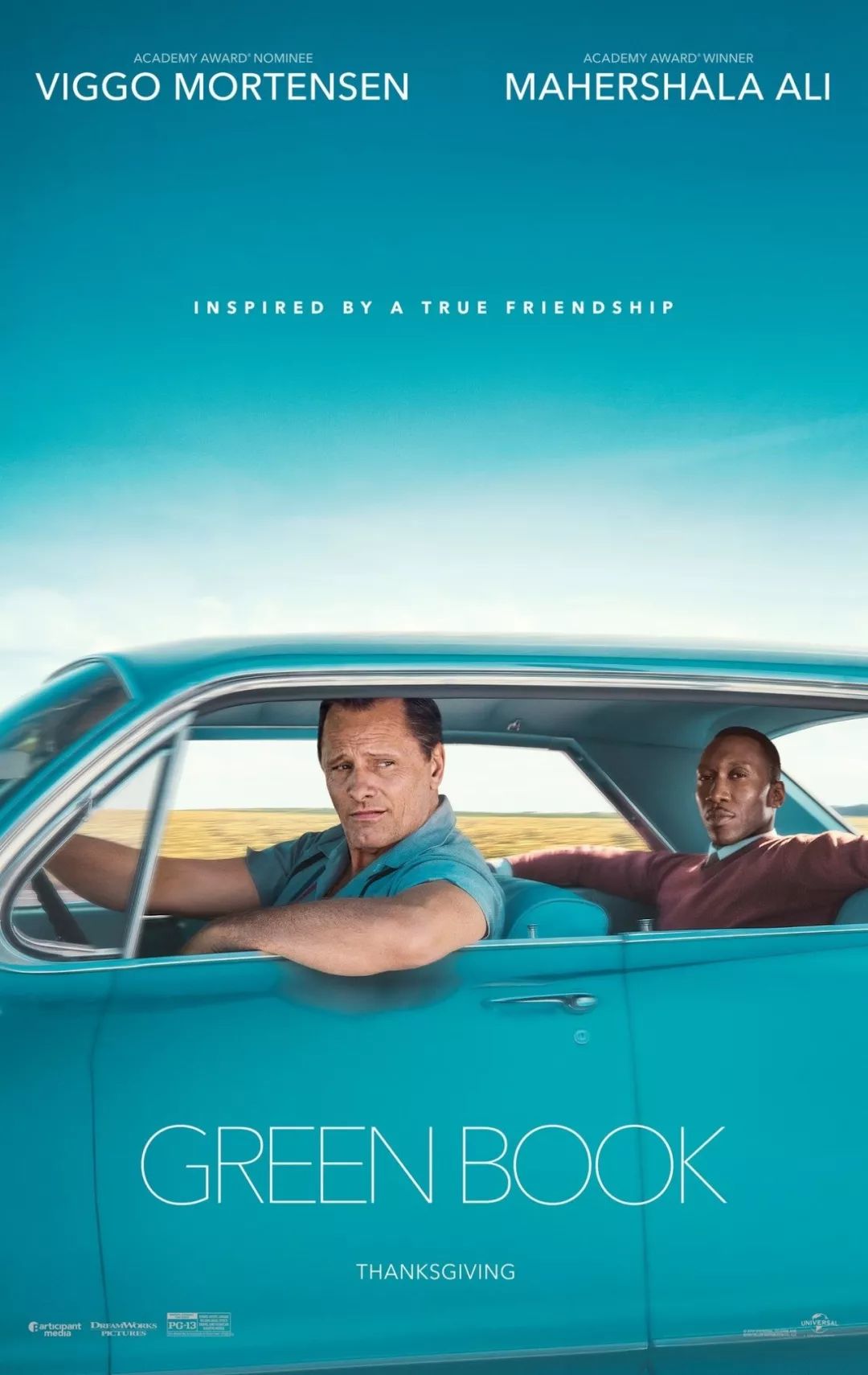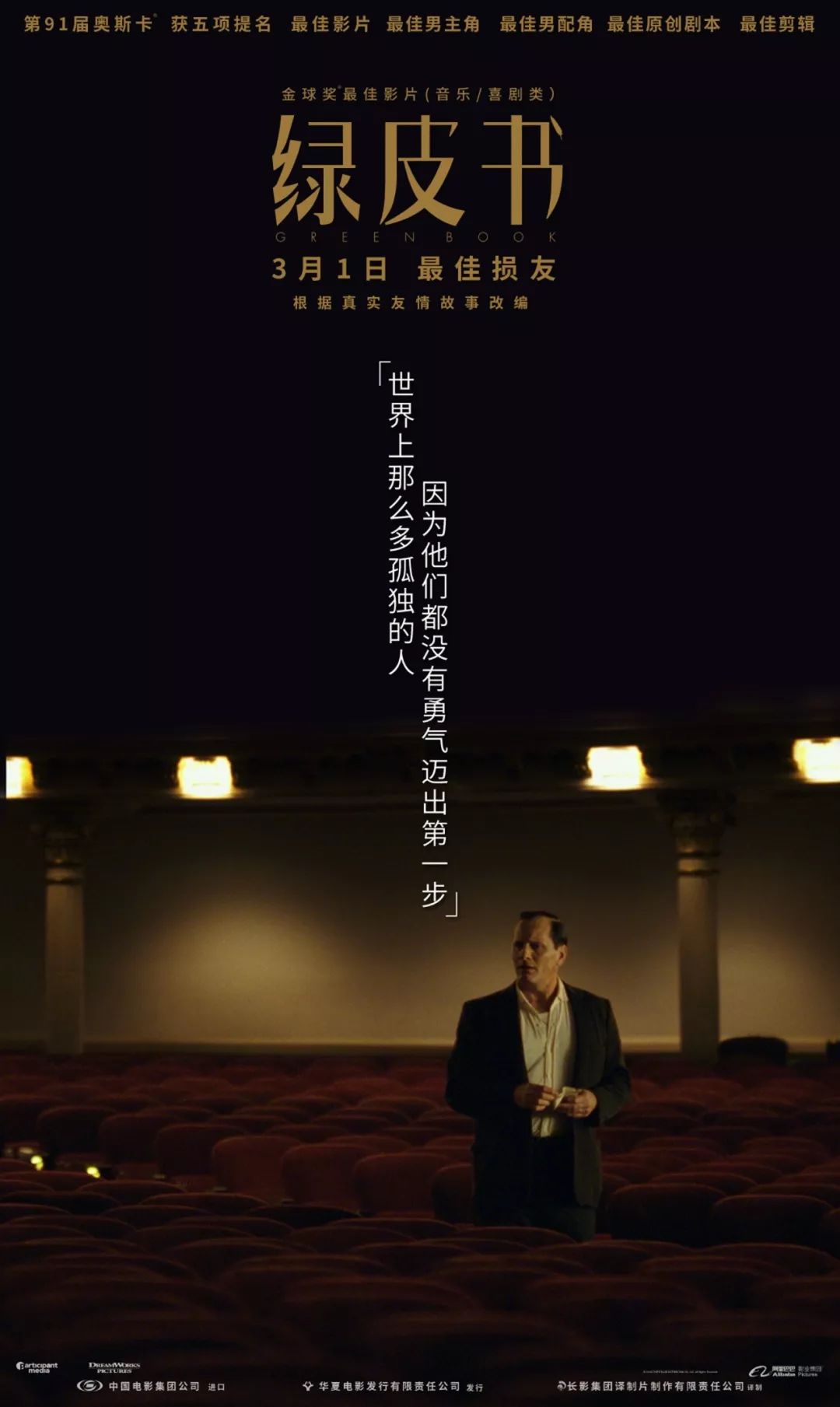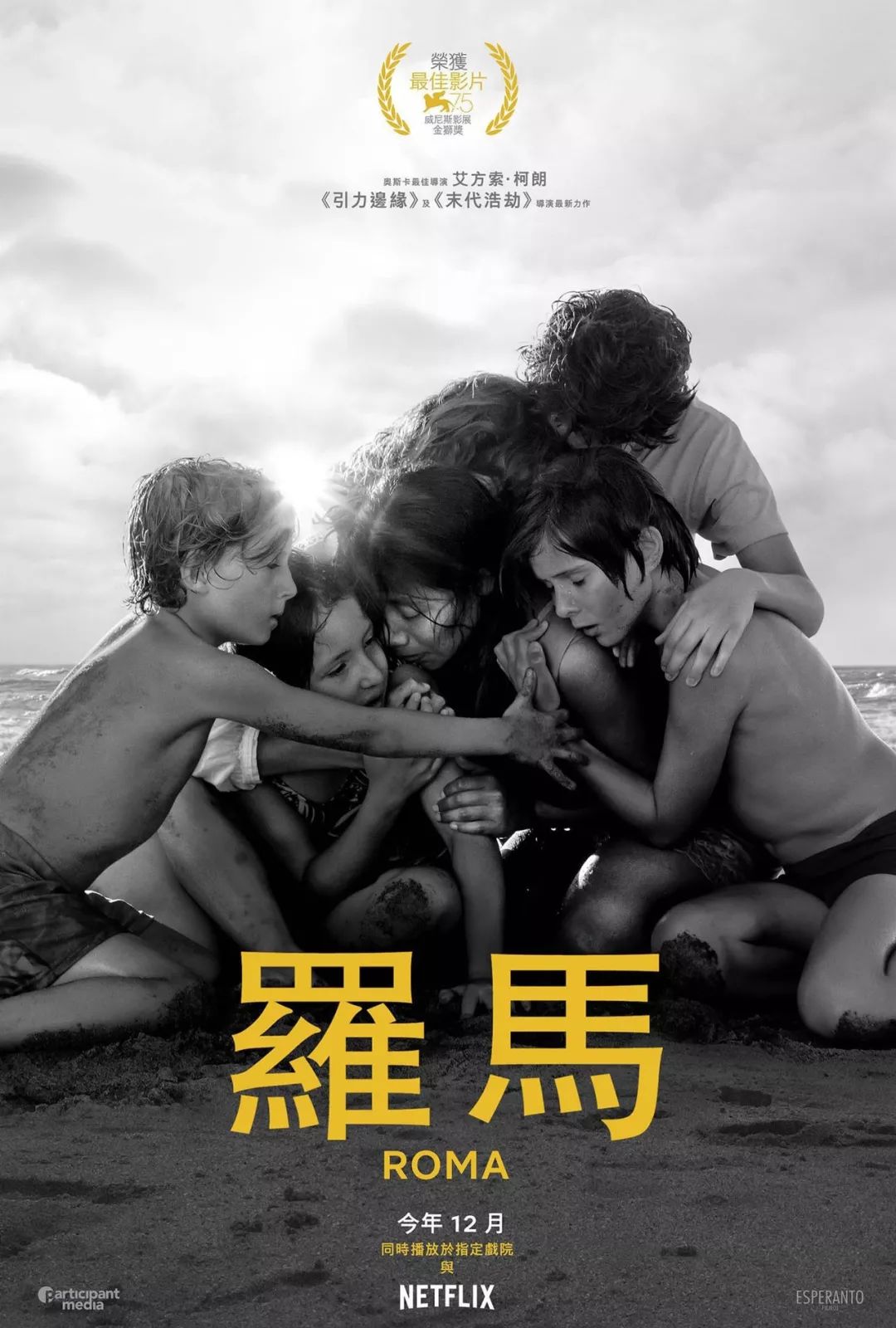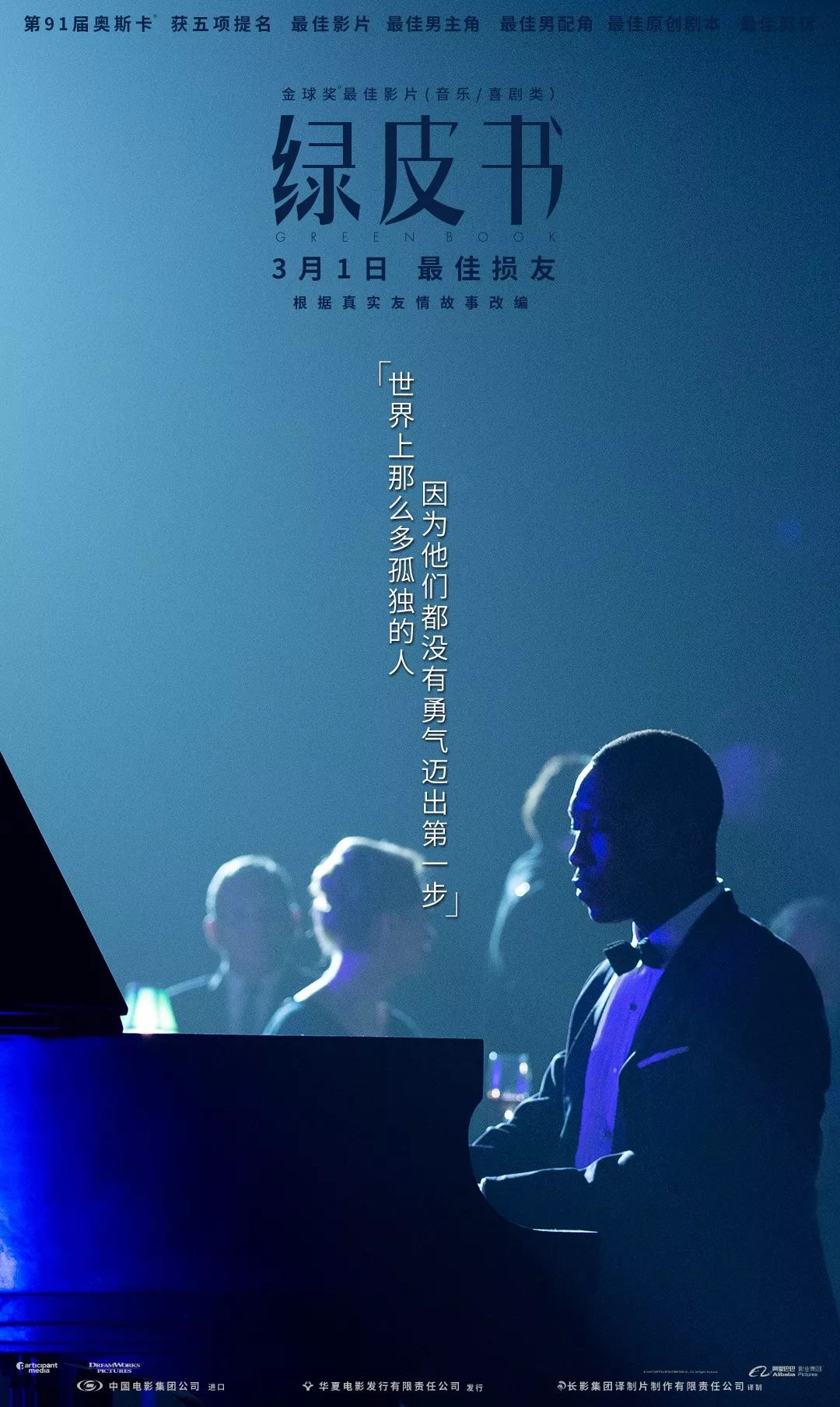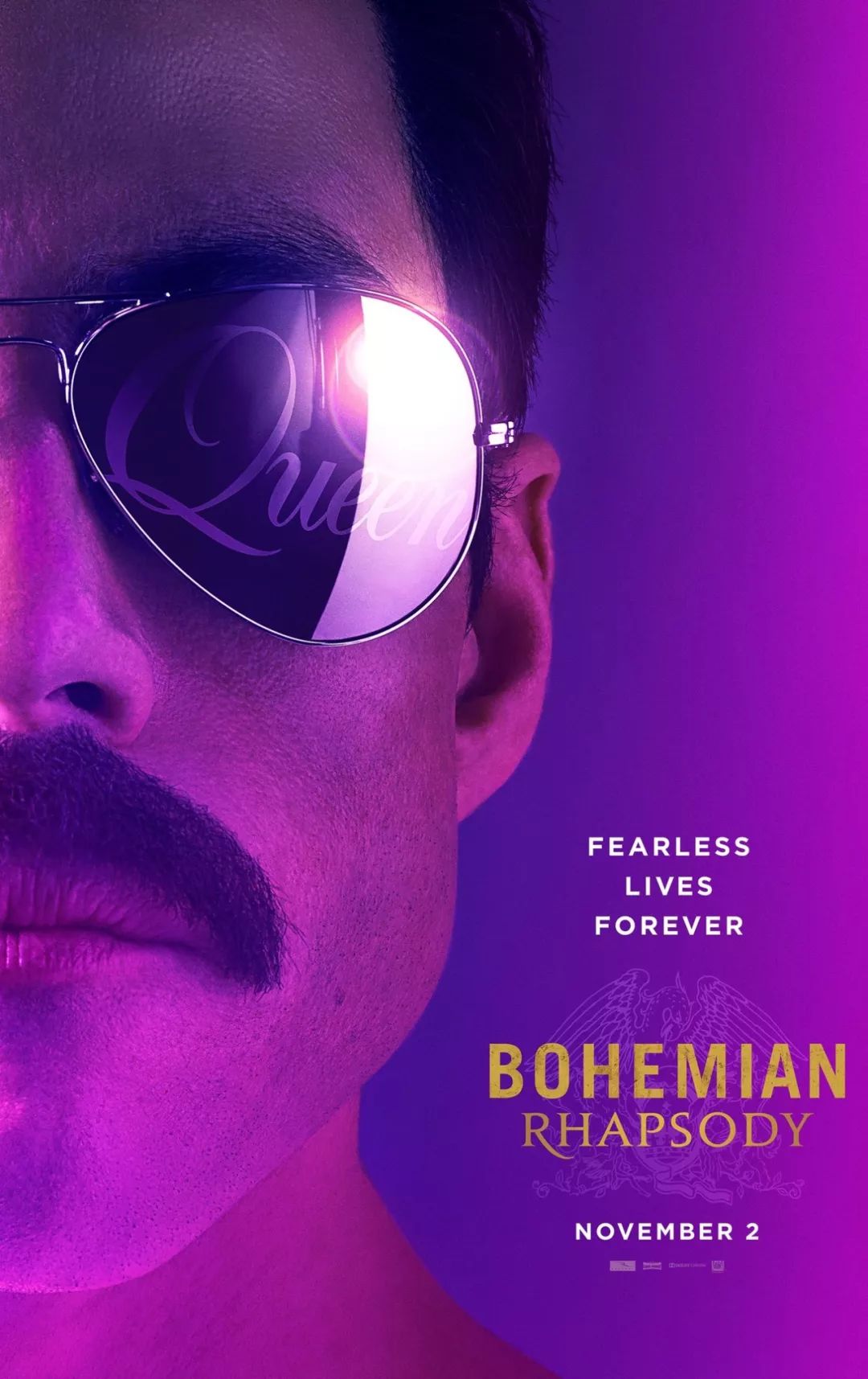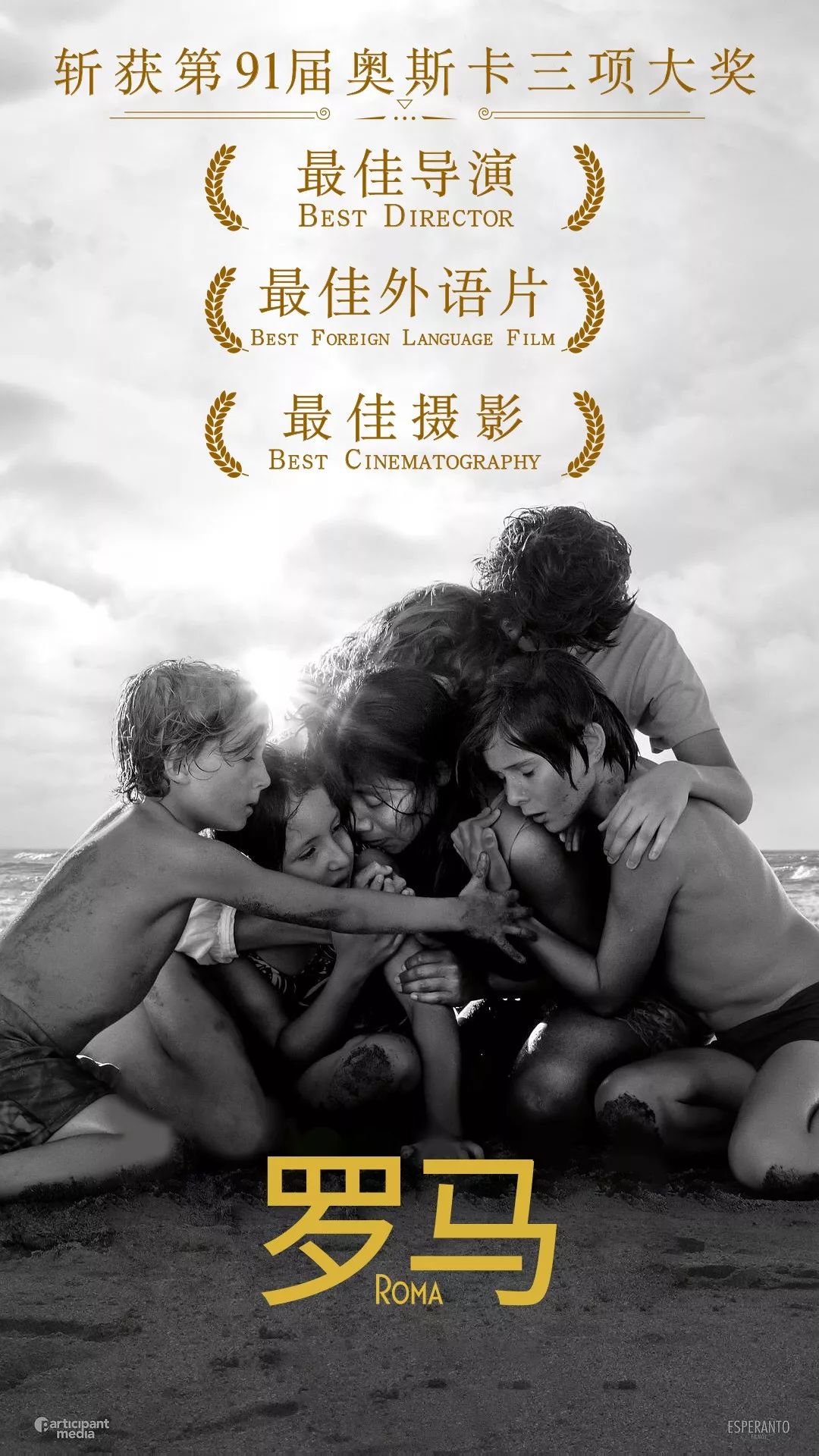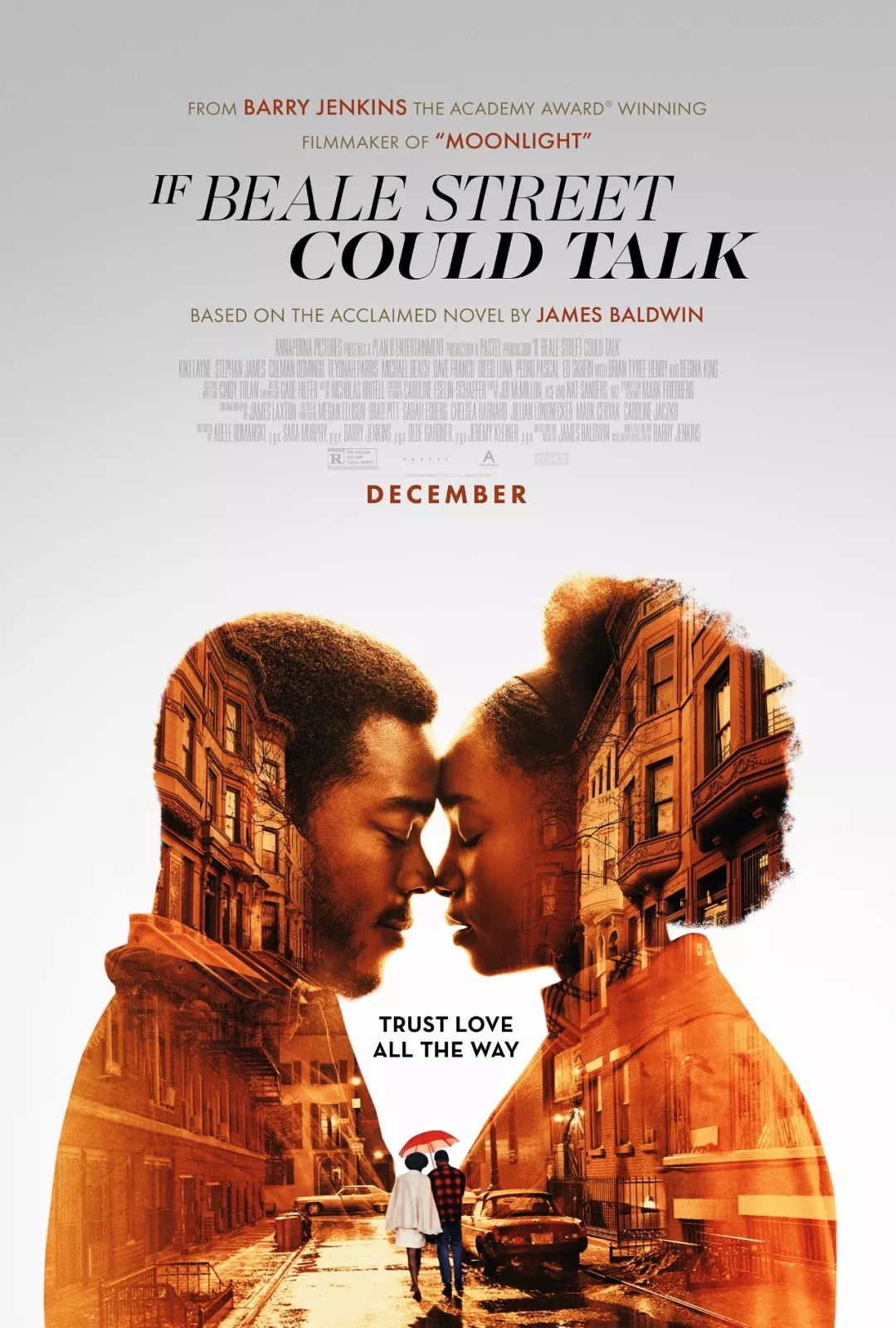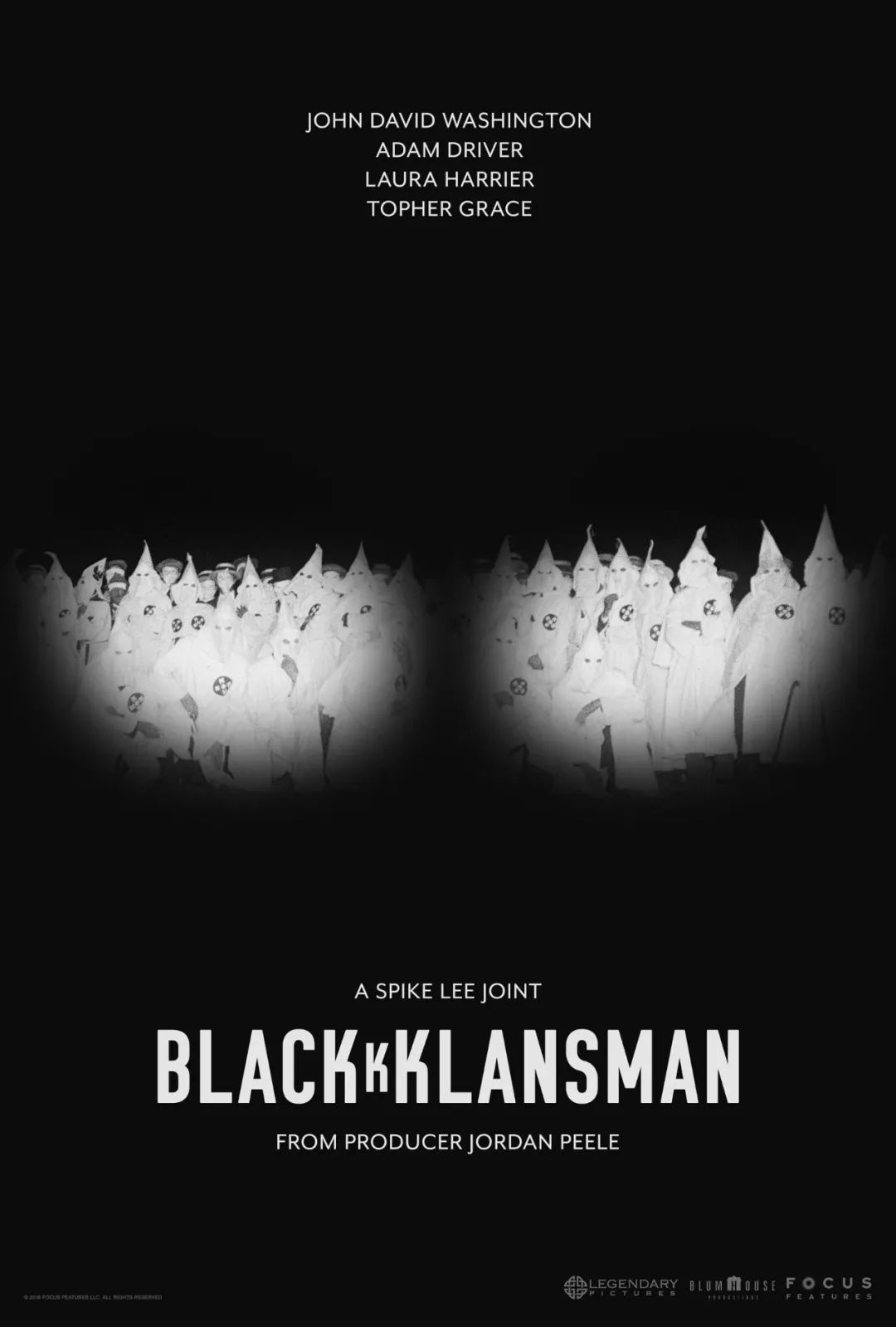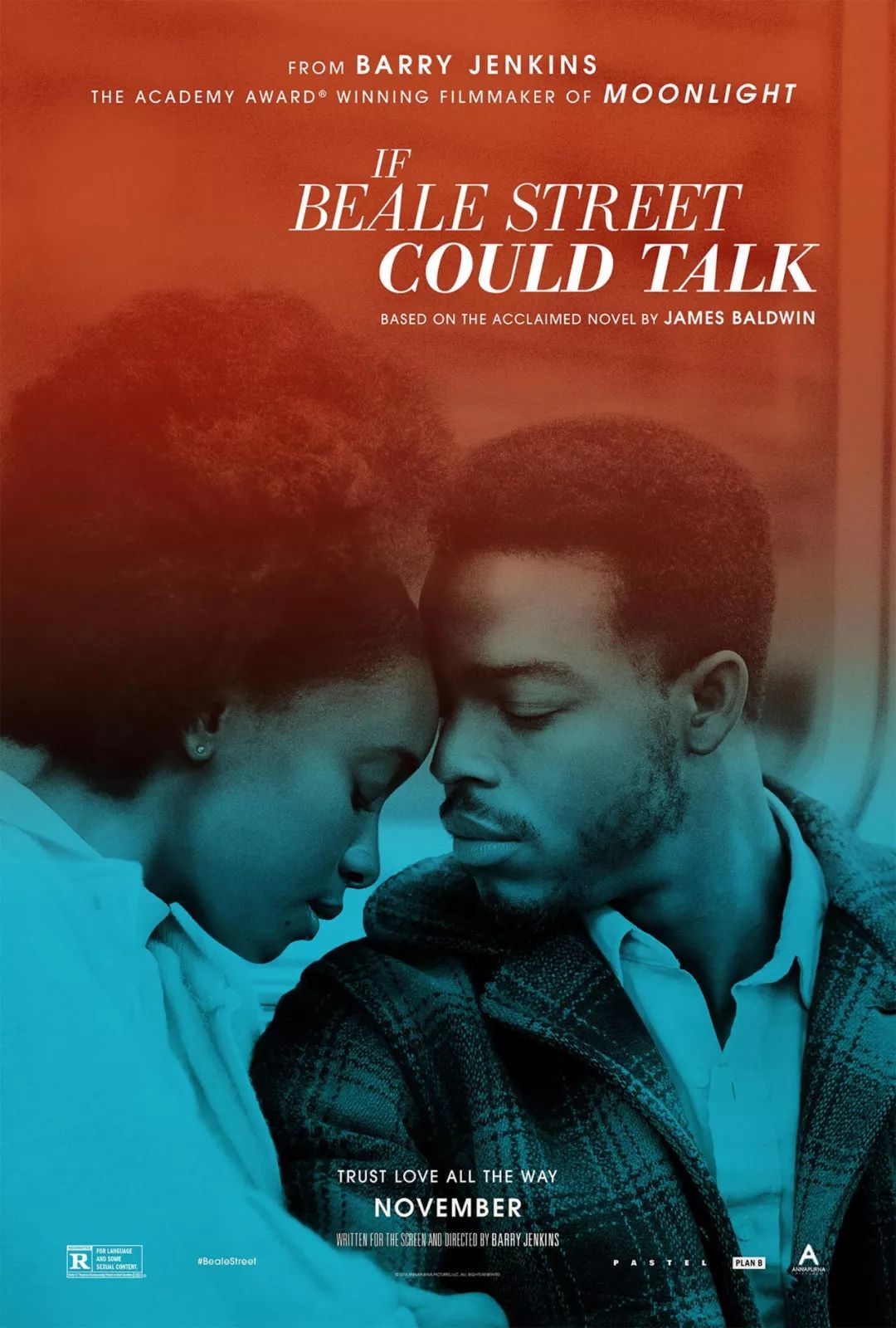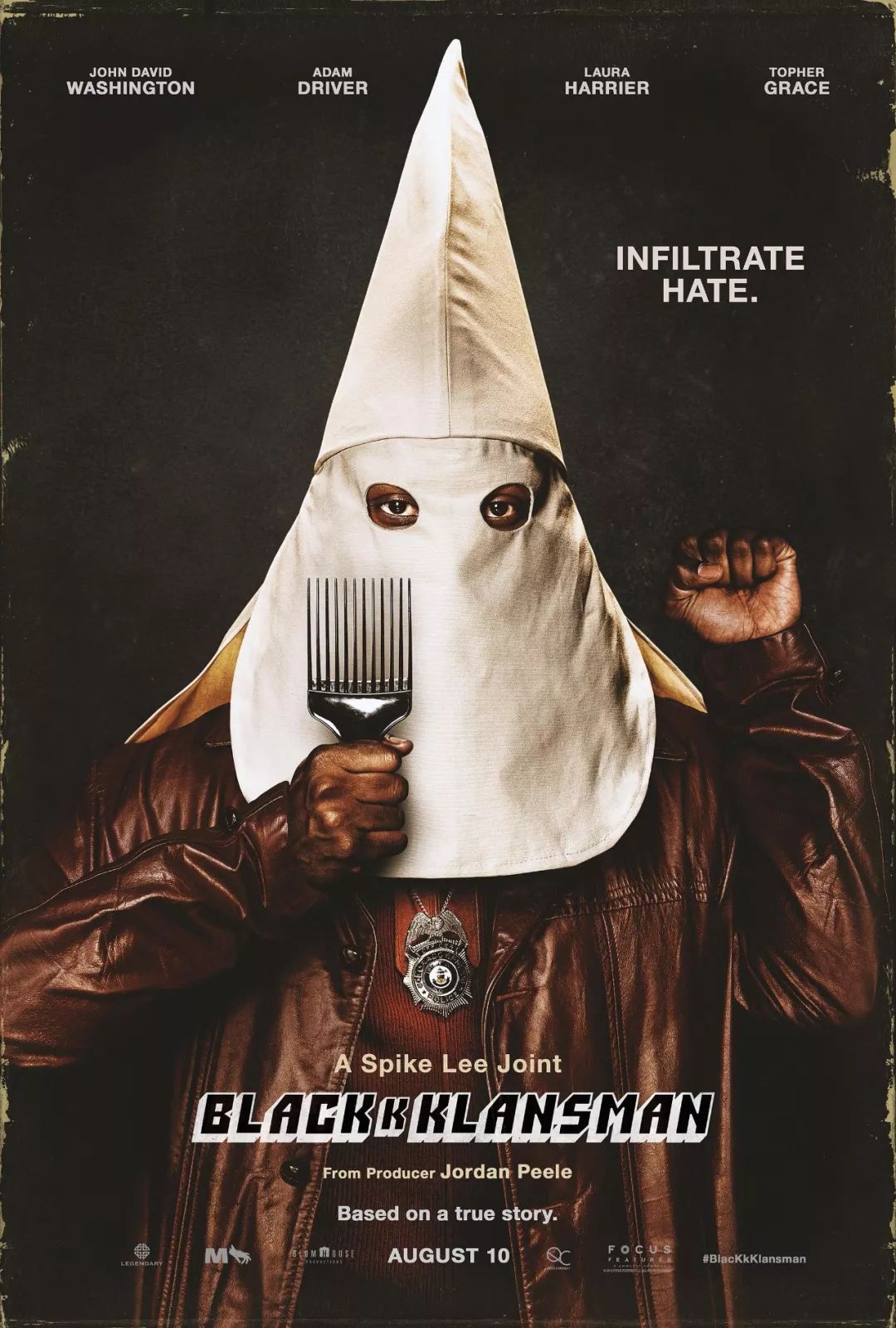
那些奥斯卡获奖的电影海报分享
小清新的《绿皮书》
获得最佳影片、最佳原创剧本、最佳男配三项大奖的《绿皮书》,海报布局也很清新,无衬线字体,适当留白,让人的视觉焦点不自觉地向下。
韩版虽然给字体多加了一种色,版式也略有调整,但主基调依然没变,正面教材~
有正面就有反面,这么多字体,这么多文案,这么多颜色,看着就闹心!
走安安静静的路线不好嘛~
聚拢的《罗马》
阿方索·卡隆也是凭《罗马》斩获最佳导演、最佳摄影及最佳外语片三项大奖!海报是典型的三角形构图,字体也呈细长、高低状的。
韩版依然吸收了原版的精髓~
可中文版就完全打破了这种感觉,跟画面格格不入!
不仅如此,还给你搞乱画面,感觉人被字挤得不行不行了,好可怜~
紫外光的《波西米亚狂想曲》
凭借《波西米亚狂想曲》,拉米·马雷克喜得影帝,海报也是用尽了2018流行色——紫外光。
中文版,也没有车祸~
还用了最流行的海报排版方式~
还有留白、渲染,真的很美~
最喜欢这张,不管是字体,还是色彩,都恰到好处~
曝光的《假若比尔街能说话》
雷吉娜·金获得了这部影片的最佳女配角,海报虽然没有特别大的亮点,但好在也没有出错,正片叠底、双重曝光都用上了。
最佳海报的《黑色党徒》
《黑色党徒》 虽然只获得了最佳改编剧本,但它的海报却很精彩,获得了2018最佳电影海报前20名。
每一张的设计,你都可以学习借鉴。
黑白金的《一个明星的诞生》
本来这部影片,只获得了最佳原创歌曲:“Shallow”,海报也是简单的黑白灰,但金色的衬线字体排版,稍显设计感~
可事实证明,有些排版只适合西文~
原汁原味的《登月第一人》
获得最佳视觉效果的《登月第一人》,第一眼就是流浪地球的即时感,不过人家才是原版。
字体好看的《黑豹》
最后一部《黑豹》,斩获最佳服装设计、最佳原创配乐、最佳艺术指导,不过我觉得还得加一个,就是最佳字体,字由上有这款,叫BEYNO,商用免费哦~